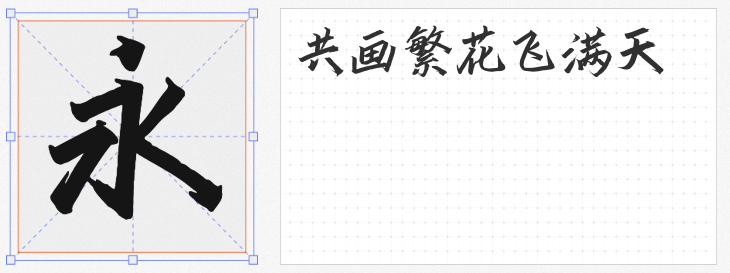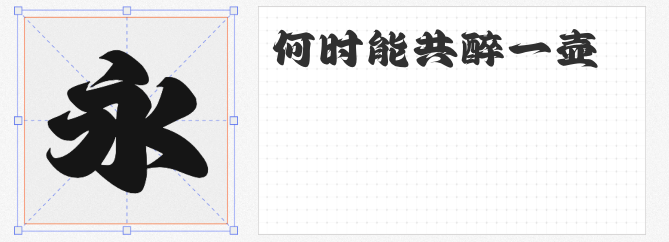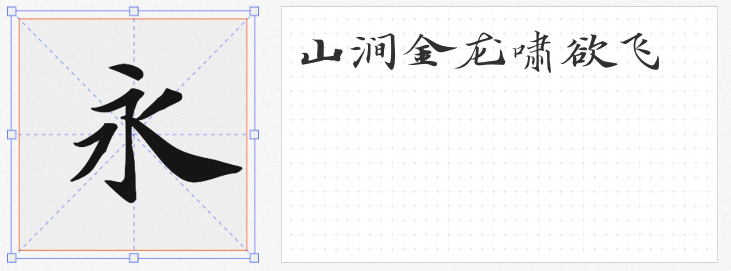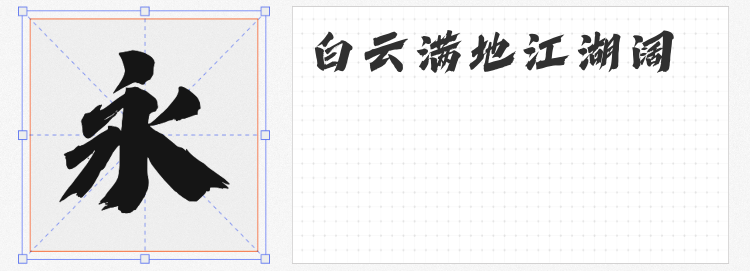
在国风设计浪潮中,字体不仅是信息载体,更是文化意境的延伸。以下四款商用字库字体,以独特的书法韵味与现代设计语言,为白酒包装、文化展览、影视海报等场景注入东方美学灵魂。
这款毛笔楷书字体以“醉酒挥毫”为灵感,收笔如刀锋凌厉,笔法正统中透出江湖侠客的洒脱不羁。其字形结构保留传统行楷的遒劲,同时通过夸张的笔画粗细对比(如竖画如剑、捺画似刀)强化视觉冲击力。在白酒包装设计中,它能瞬间传递“烈酒入喉,豪情万丈”的意境;应用于武侠题材海报时,更可与山水泼墨背景相得益彰,营造刀光剑影的江湖氛围。
基于敦煌写经小楷改良的这款字体,以右向倾斜的动态结构打破传统楷书的静态感。横细竖粗的对比与主笔(如捺画、挑勾)的夸张延伸,既保留了经卷书法的肃穆,又赋予飘逸灵动的现代审美。在茶文化海报中,其清秀字形可与水墨茶具图案呼应;用于古籍展览宣传时,则能还原“千年藏经,一卷千年”的历史厚重感。
灵感源自日本江户时代勘亭流广告字体的这款创意字,通过“圆润敦厚”的字形与“满”字布白法则,构建出独特的视觉张力。其结体方正中宫宽博,用笔敦厚有力却不失轻盈,既承载了传统书法的烟火气,又融入现代设计的留白哲学。在国潮品牌海报中,它能与几何图形、金属质感元素碰撞出复古未来感;用于餐饮行业设计时,则可传递“市井烟火,人间至味”的温暖意象。
这款字体以“行草入楷”的笔法突破传统书体的束缚,落笔如铁画银钩,收放间尽显侠者风范。其字形浑厚却不臃肿,通过笔画粗细的自然过渡(如横画由细渐粗、竖画由重转轻)营造动态平衡。在影视海报设计中,它能与武侠人物剪影、水墨剑气背景形成强烈视觉呼应;用于运动品牌宣传时,则可传递“突破极限,行者无疆”的品牌精神。
四款字体各具风骨,却共同诠释了国风设计的核心——以传统为根,以创新为翼。无论是追求豪情万丈的江湖气,还是钟爱清逸脱俗的文人韵,亦或是向往古今交融的跨界美学,这些商用字库均能以精准的笔触,为设计注入灵魂。